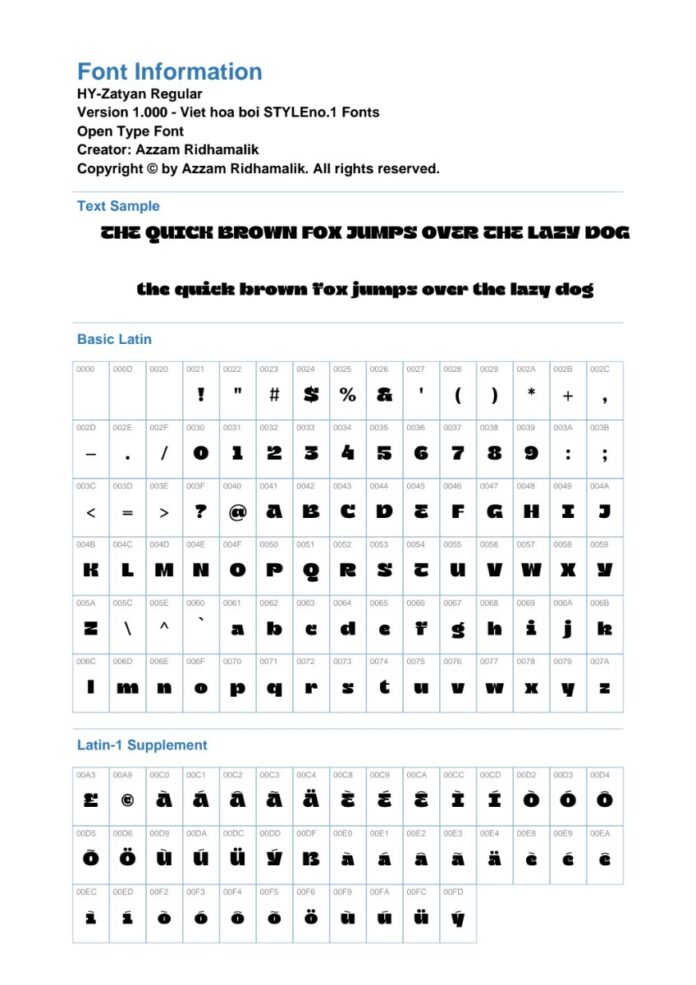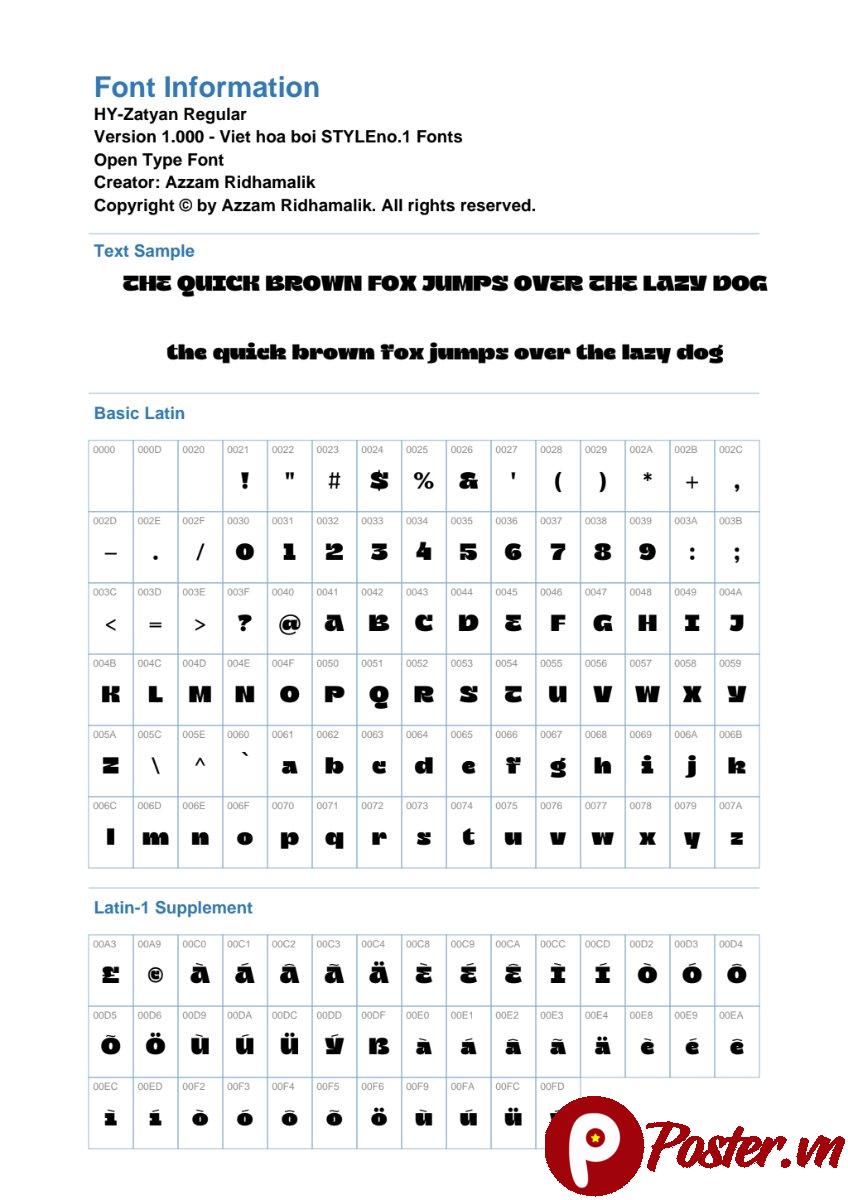
Font HY-Zatyan: Đậm chất cá tính
Trong thế giới thiết kế đồ họa, việc lựa chọn font chữ phù hợp có thể tạo nên sự khác biệt lớn cho bất kỳ dự án nào. Và khi nói đến những kiểu chữ mang đậm dấu ấn cá nhân, mạnh mẽ và độc đáo, Font HY-Zatyan chắc chắn là một cái tên không thể bỏ qua. Với thiết kế đặc trưng, font chữ này hứa hẹn sẽ mang đến một làn gió mới cho các tác phẩm sáng tạo của bạn.
Giới thiệu về Font HY-Zatyan
Font HY-Zatyan là một kiểu chữ Open Type được phát triển bởi Azzam Ridhamalik, thuộc bộ sưu tập HY-Zatyan Regular. Với phiên bản 1.000, font này được thiết kế với phong cách mạnh mẽ, các nét chữ dày dặn và có phần góc cạnh, tạo cảm giác vững chãi và đầy cá tính. Đây là lựa chọn lý tưởng cho những ai muốn tạo điểm nhấn ấn tượng trong các thiết kế của mình.
Đặc điểm nổi bật của Font HY-Zatyan
• Thiết kế độc đáo: HY-Zatyan sở hữu những đường nét mạnh mẽ, dứt khoát, mang lại cảm giác hiện đại và năng động. Các ký tự được bo tròn nhẹ ở các góc, tạo sự mềm mại nhất định nhưng vẫn giữ được vẻ cứng cáp tổng thể.
• Tính ứng dụng cao: Mặc dù có phong cách đặc trưng, HY-Zatyan vẫn rất linh hoạt trong nhiều loại hình thiết kế khác nhau, từ tiêu đề, logo, poster, banner đến các ấn phẩm quảng cáo, bao bì sản phẩm.
• Hỗ trợ đa ngôn ngữ: Font này không chỉ hỗ trợ Basic Latin mà còn có Latin-1 Supplement, giúp người dùng có thể sử dụng cho nhiều ngôn ngữ khác nhau, bao gồm cả tiếng Việt (với một số ký tự đặc biệt).
Ứng dụng của Font HY-Zatyan trong thiết kế
Với những đặc điểm nổi bật của mình, Font HY-Zatyan có thể được ứng dụng rộng rãi trong nhiều lĩnh vực:
Thiết kế Logo và Nhận diện thương hiệu
Sự mạnh mẽ và độc đáo của HY-Zatyan rất phù hợp để tạo ra các logo ấn tượng, giúp thương hiệu của bạn nổi bật và dễ nhận diện. Các công ty công nghệ, thời trang đường phố, hoặc các thương hiệu muốn thể hiện sự cá tính, năng động sẽ tìm thấy giá trị lớn ở font chữ này.
Thiết kế Poster, Banner và Quảng cáo
Trong các ấn phẩm quảng cáo, tiêu đề cần phải thật sự thu hút và dễ đọc. Font HY-Zatyan với các nét chữ dày sẽ giúp thông điệp của bạn nổi bật trên mọi nền tảng, từ poster in ấn đến banner kỹ thuật số. Nó đặc biệt hiệu quả khi sử dụng cho các sự kiện âm nhạc, thể thao hoặc các chiến dịch khuyến mãi cần sự mạnh mẽ.
Thiết kế Bao bì sản phẩm
Để tạo sự khác biệt cho sản phẩm trên kệ hàng, bao bì đóng vai trò cực kỳ quan trọng. Font HY-Zatyan có thể giúp sản phẩm của bạn trông hiện đại, mạnh mẽ và thu hút hơn, đặc biệt là với các sản phẩm dành cho giới trẻ hoặc các ngành hàng như đồ uống năng lượng, thực phẩm bổ sung.
Thiết kế Tiêu đề sách, tạp chí
Với các ấn phẩm in ấn như sách, tạp chí, việc sử dụng một font chữ độc đáo cho tiêu đề có thể tạo nên sự hấp dẫn ngay từ cái nhìn đầu tiên. HY-Zatyan mang đến sự phá cách, giúp các tiêu đề trở nên sống động và lôi cuốn hơn.
Hướng dẫn sử dụng Font HY-Zatyan hiệu quả
Để tận dụng tối đa vẻ đẹp của Font HY-Zatyan, bạn có thể tham khảo một số gợi ý sau:
Kết hợp với các font chữ khác
Vì HY-Zatyan có phong cách khá mạnh mẽ, bạn nên kết hợp nó với các font chữ đơn giản, dễ đọc hơn cho phần nội dung chính. Các font sans-serif hoặc serif cơ bản sẽ tạo sự cân bằng và giúp tổng thể thiết kế hài hòa hơn.
Lựa chọn màu sắc phù hợp
Màu sắc đóng vai trò quan trọng trong việc làm nổi bật font chữ. Với HY-Zatyan, bạn có thể thử nghiệm với các màu sắc tương phản mạnh để tạo hiệu ứng thị giác ấn tượng, hoặc sử dụng các tông màu trầm để mang lại vẻ sang trọng, bí ẩn.
Cân nhắc kích thước và khoảng cách
Do các nét chữ dày, việc điều chỉnh kích thước và khoảng cách giữa các ký tự (kerning) và dòng (leading) là rất quan trọng để đảm bảo tính dễ đọc. Hãy thử nghiệm để tìm ra tỷ lệ tối ưu cho thiết kế của bạn.
Kết luận